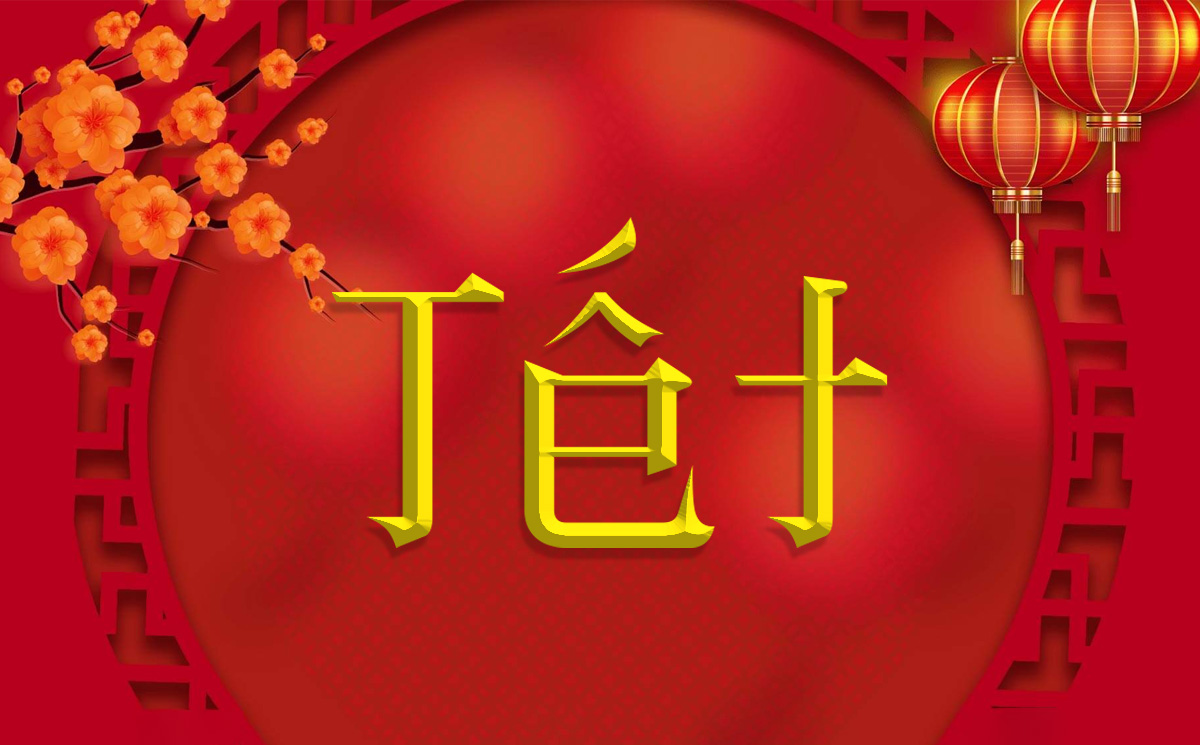
Phân loại các nhóm font chữ Tết đẹp và phổ biến nhất
Để truyền tải chính xác tinh thần của mùa xuân, việc lựa chọn đúng phong cách Typography cho từng loại ấn phẩm bao bì là điều vô cùng quan trọng.
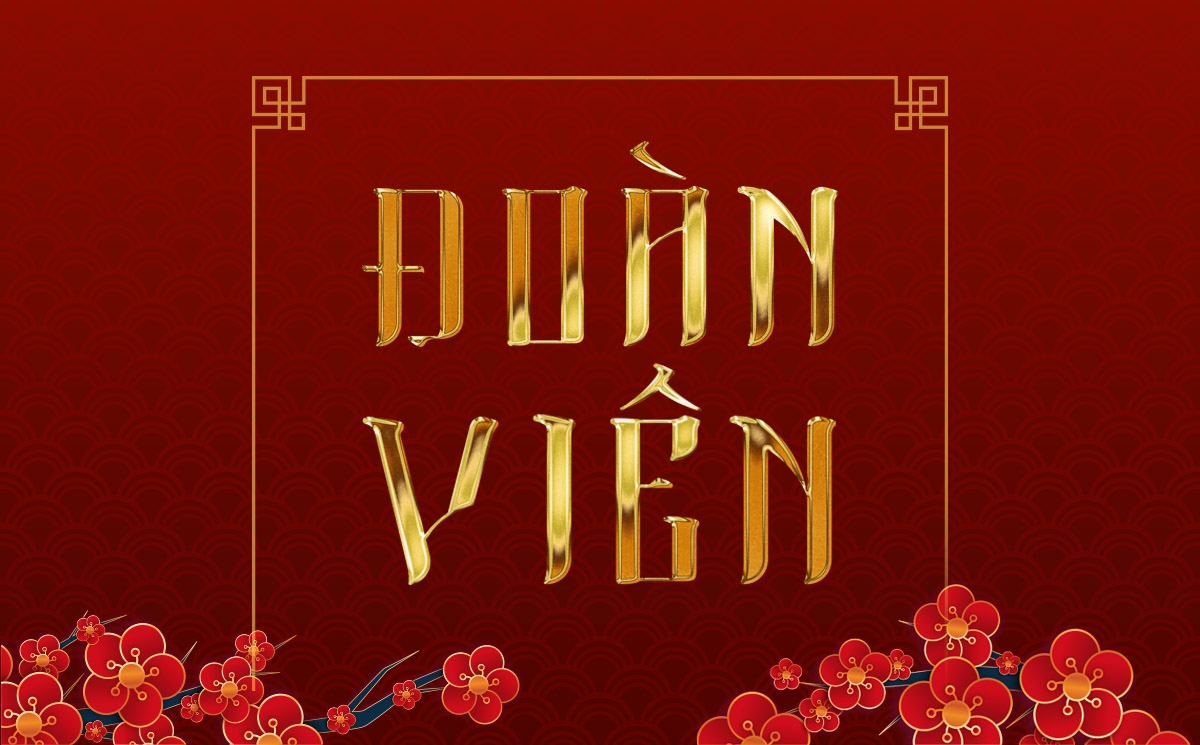
Nhóm font Thư pháp truyền thống (Calligraphy)
Đặc trưng lớn nhất của nhóm này là những nét bút lông đẫm mực, uốn lượn bay bổng mô phỏng các câu đối đỏ ngày xuân. Khi sử dụng các mẫu Font chữ Tết Việt hóa dòng thư pháp, các từ khóa như “An Khang Thịnh Vượng”, “Vạn Sự Như Ý” sẽ ngay lập tức mang lại cảm giác hoài cổ, trang trọng và đậm đà bản sắc truyền thống, rất hoàn hảo cho bao lì xì và nắp hộp quà Tết.
Nhóm font chữ Tết hiện đại và phá cách (Modern Display)
Bên cạnh phong cách truyền thống, xu hướng thiết kế bao bì Tết những năm gần đây ưa chuộng các dòng Font chữ Tết đẹp mang tính hình học hoặc nét béo mập (Chunky Display). Các phông chữ này có cấu trúc dày dặn, các góc bo tròn thân thiện hoặc nét cắt vát sắc sảo, giúp các chiến dịch quảng cáo xuân của các thương hiệu trẻ trở nên năng động, bắt mắt và thời thượng hơn.
Ưu điểm nổi bật của các bản font chữ Tết Việt hóa
Khi ứng dụng các phông chữ chủ đề lễ hội vào thị trường trong nước, sự chỉn chu về dấu câu là yếu tố quyết định đến tính chuyên nghiệp của bản thiết kế:
- Khắc phục triệt để lỗi dấu tiếng Việt: Phiên bản Font chữ Tết đẹp Free đã được đội ngũ thiết kế trau chuốt thủ công từng dấu câu. Các dấu sắc, huyền, hỏi, ngã, nặng được vẽ đồng điệu cùng thân chữ gốc, không gây cảm giác chắp vá hay đè nét làm mất tính thẩm mỹ.
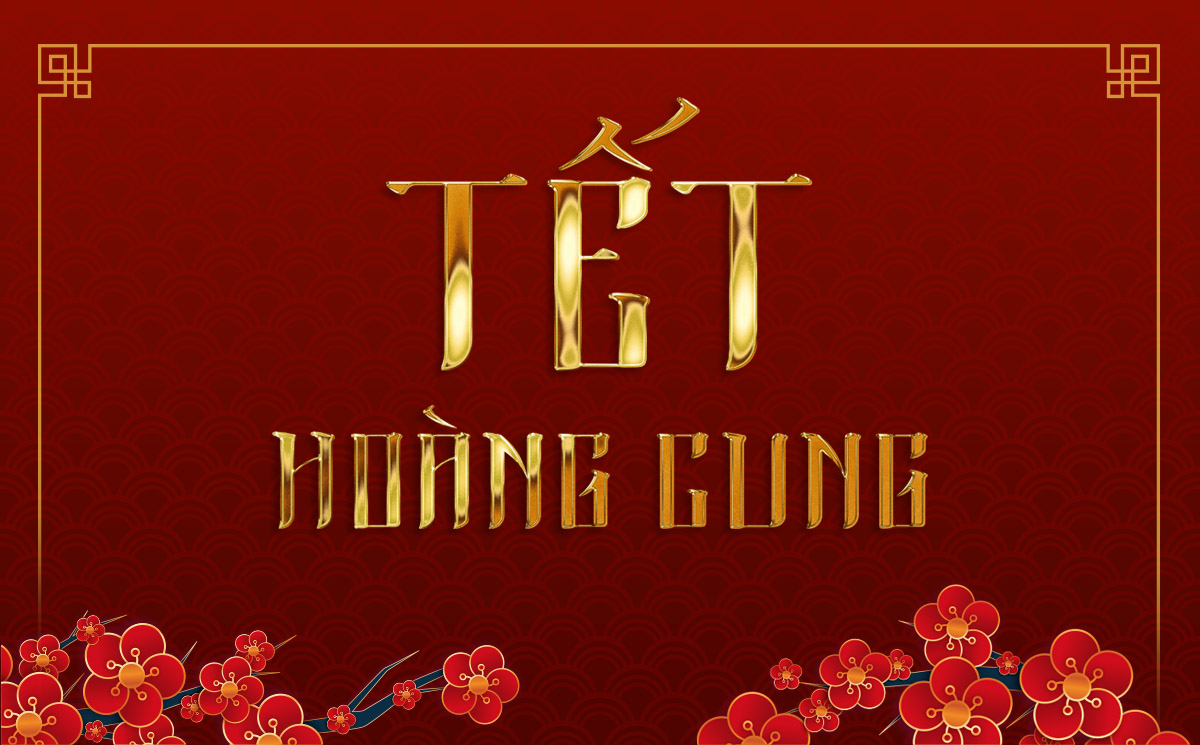
| Phong cách Font | Đặc điểm thị giác | Ứng dụng đề xuất tại Doozypack.vn |
| Thư pháp truyền thống | Bay bổng, nét bút lông uy nghi | In bao lì xì, câu đối, tiêu đề hộp quà Tết truyền thống. |
| Font Tết hiện đại (Display) | Dày dặn, mập mạp, vui tươi | Bao bì bánh kẹo Tết, hộp quà doanh nghiệp trẻ trung. |
| Font Retro Sài Gòn xưa | Hoài cổ, nét dày, vững chãi | Tem nhãn hộp trà, cà phê biếu Tết, túi giấy sự kiện xuân. |